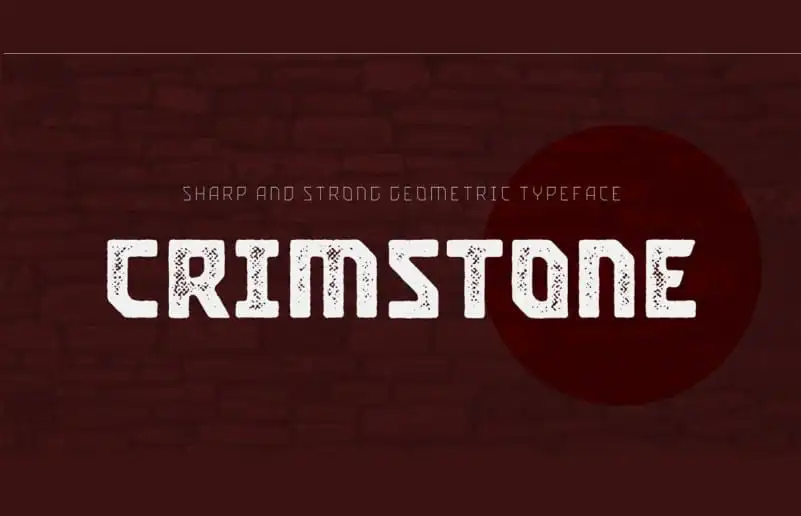
A Crimstone Display Font é uma elegante escolha para projetos visuais modernos e inovadores. Inspirada em futurismo tecnológico, essa fonte oferece um visual poderoso com ângulos rígidos e retangulares que se aproximam da realidade, recriando um futuro distante que todos compartilham. Ela é perfeita para aplicar em trabalhos de marketing, como cartazes, headlines e títulos de filmes ou até mesmo nas embalagens de produtos. Composta por letras maiúsculas, minúsculas, numerais, símbolos e suportando diversos idiomas, a Crimstone Display é uma escolha versátil para designers profissionais e criativos. O download inclui as versões arredondadas e itálicas da fonte, garantindo um look sofisticado que se destaca em qualquer projeto visual.